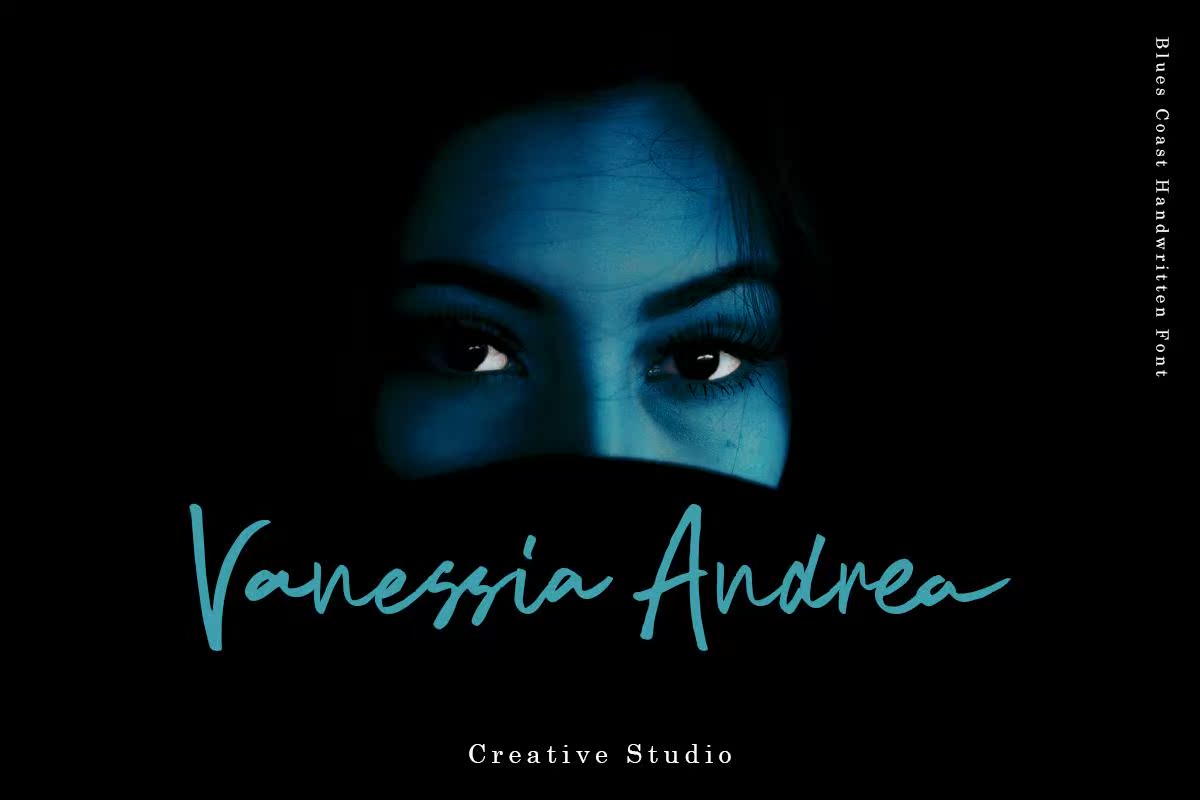
介绍BlueCoast A和WrittenFont。BlueCoast Font在移动到VectorMode之前制作和扫描了字符框。BlueCoast Font具有许多用于探索各种项目的可选字符。BlueCoast Font具有许多可选字符,如大写、小写、连字、,和Swash生成BlueCoast A并写入字体。BlueCoast Font在移动到VectorMode之前对这些和进行扫描。BlueCoast Font具有许多可用于探索各种项目的可选字符。BlueCoast Font具有许多可选字符,如大写、小写、连字和Swash